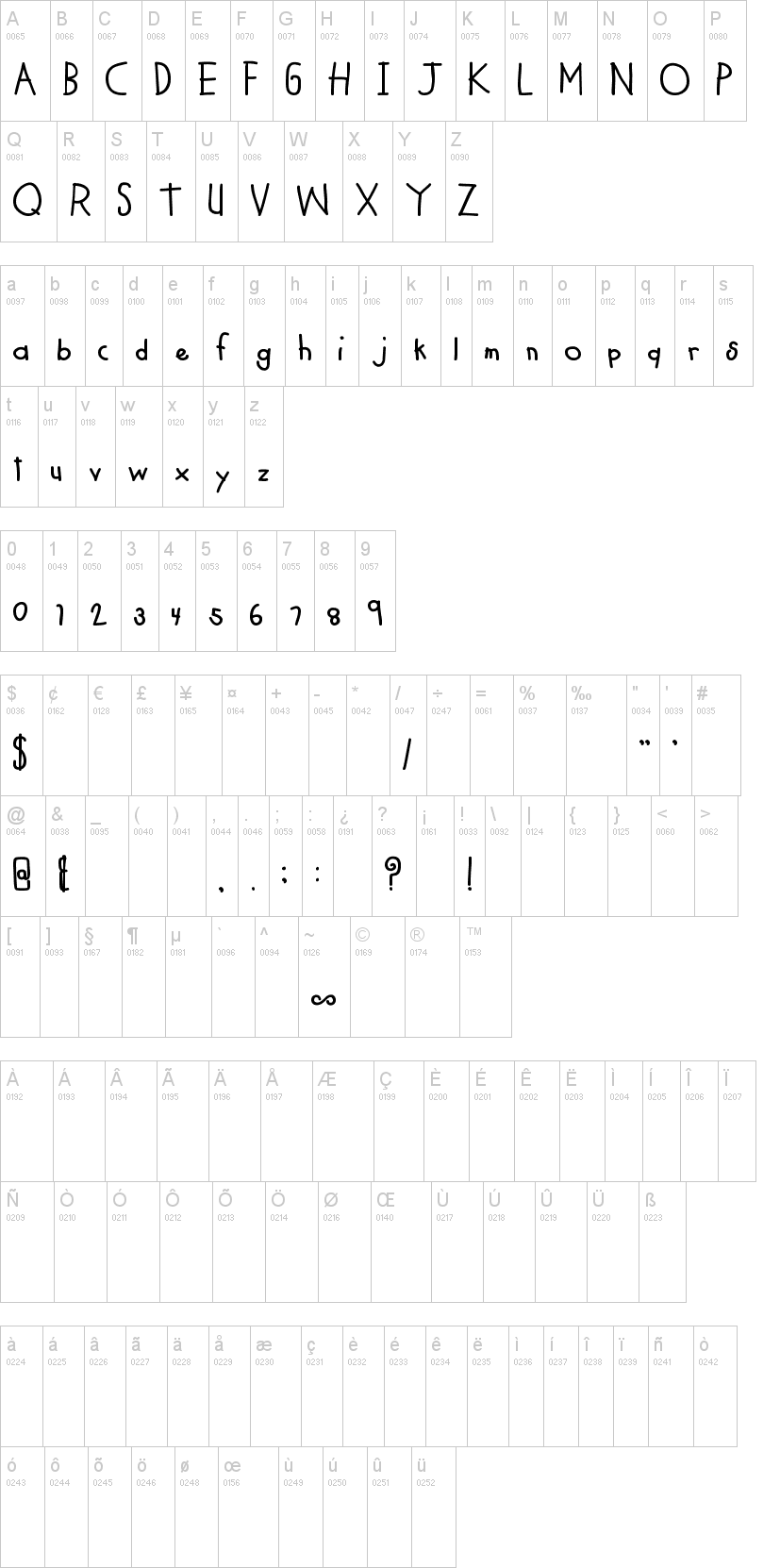
MTF Cool Kid
MTF Cool Kid是一款免费的音乐风格字体,由设计师Mtf提供。这款字体的特点是富有活力、充满趣味和时尚感,适合用于音乐、娱乐、舞蹈等领域的设计项目。字体的风格呈现出涂鸦艺术中常用的手写风格,字形较为圆润,又不失清晰度,使得整个文字看起来非常的醒目。在设计海报,广告等项目时,MTF Cool Kid 字体可以给人带来非常独特的视觉体验,从而让设计更加生动有趣。
MTF Cool Kid是一款非常不错的手写艺术字体,具有很好的视觉感,适合于文化类的宣传设计、商业类品牌的广告和产品包装设计以及个性化文字排版等较多场景。
MTF Cool Kid字符映射图